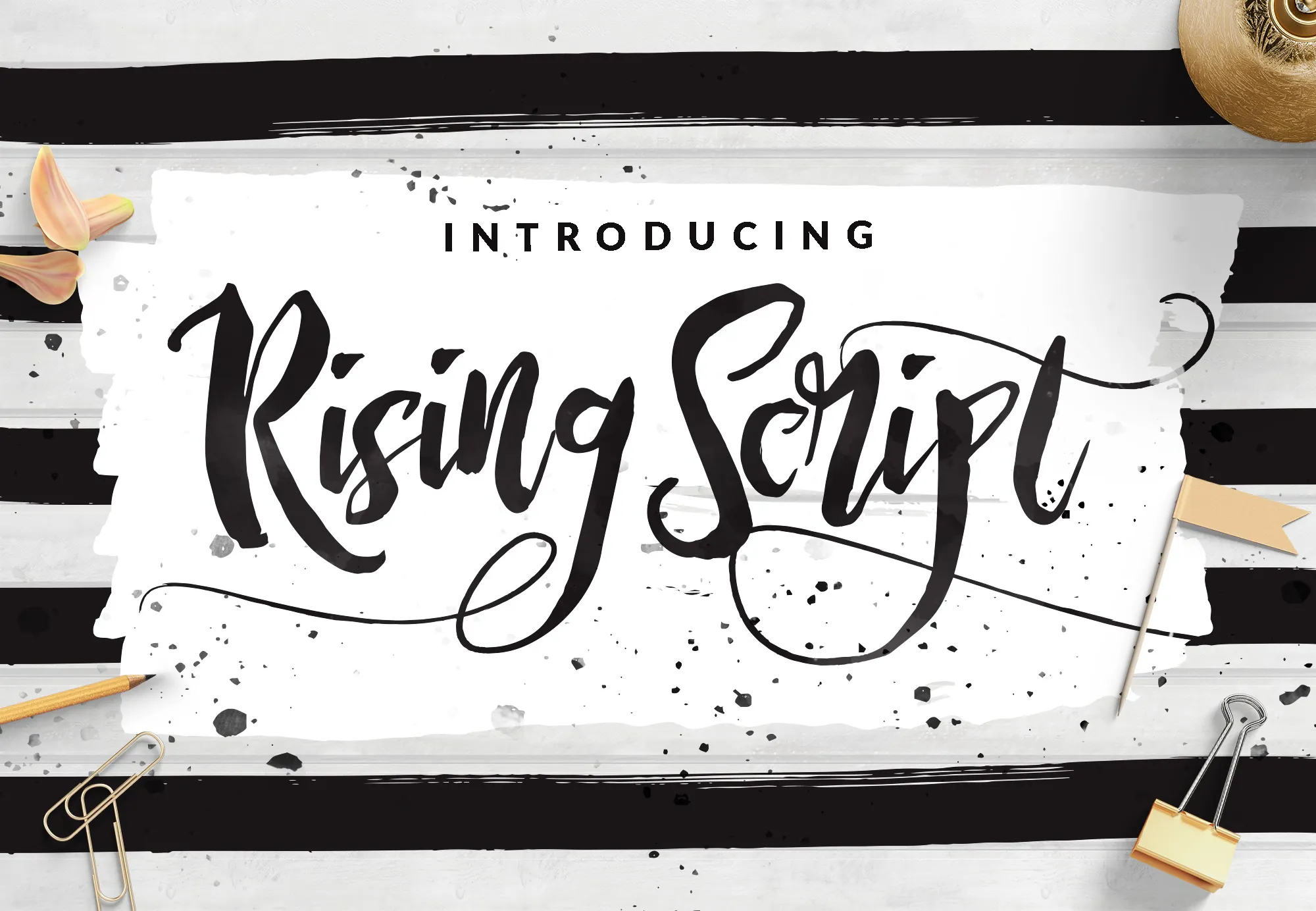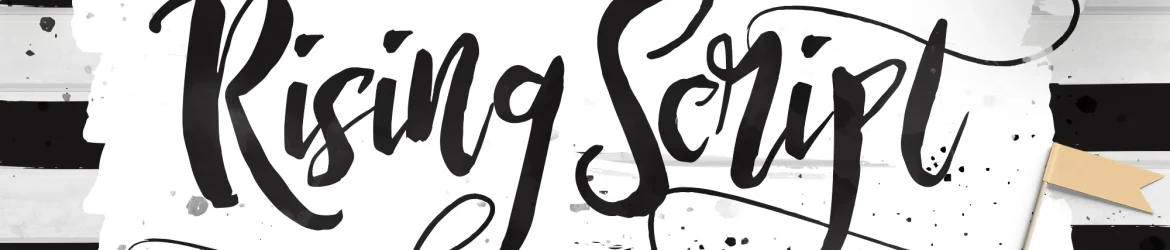
Rising Brush Font é uma fonte tipográfica que apresenta uma estética elegante e desorganizada ao mesmo tempo. Inspirada no estilo dos traços contínuos, essa fonte não segue regras e tem um aspecto de arteviseado com suas linhas não-perfeitas e seu ar quase desarranjado. Perfeito para designers de livros, capas de filmes, roupas, cartões, logotipos, fiturando e panfletos, entre outros materiais gráficos. Com seus recursos Opentype avançados, a Rising Brush Font oferece diversas alternativas incríveis para quem deseja personalizar suas criações de uma maneira única.